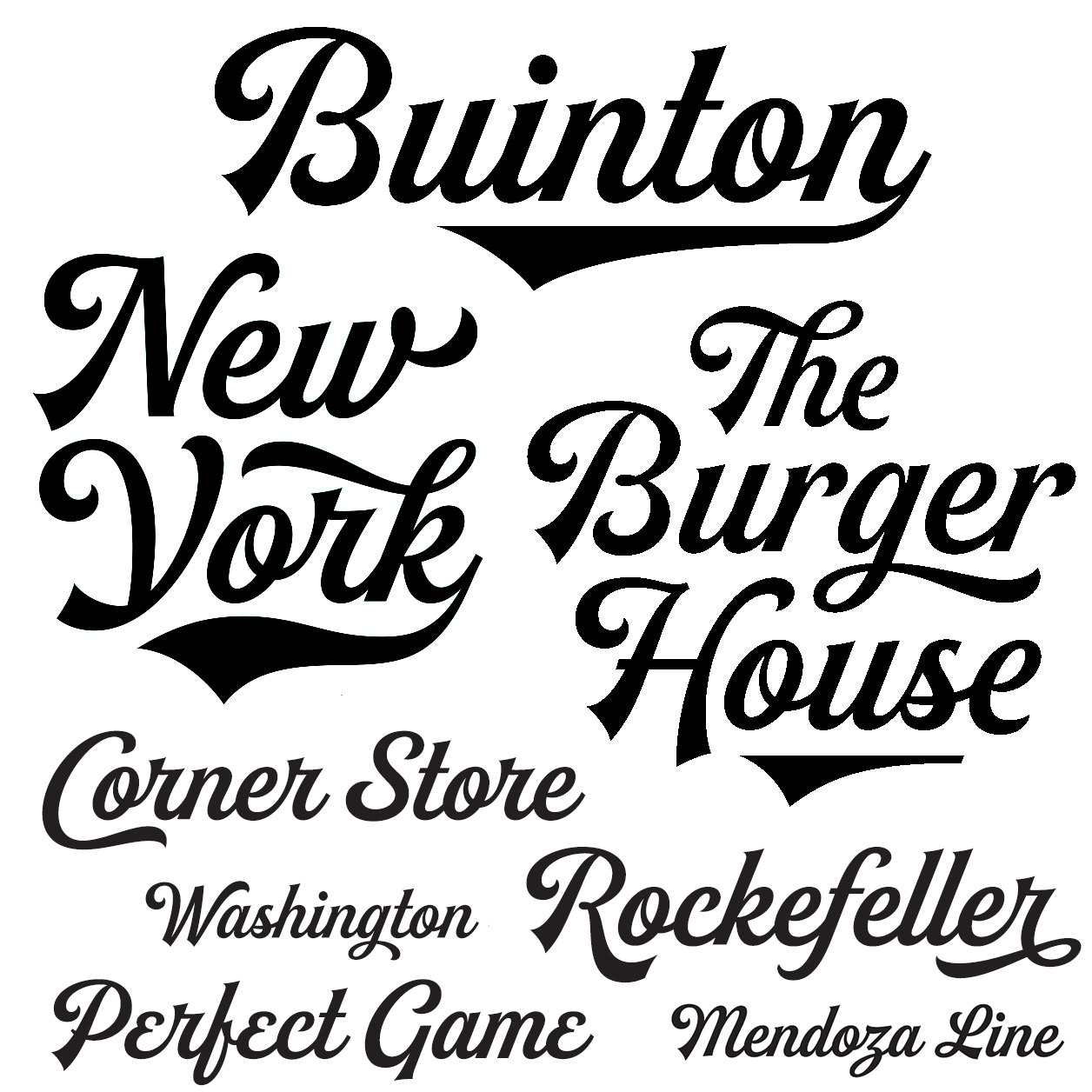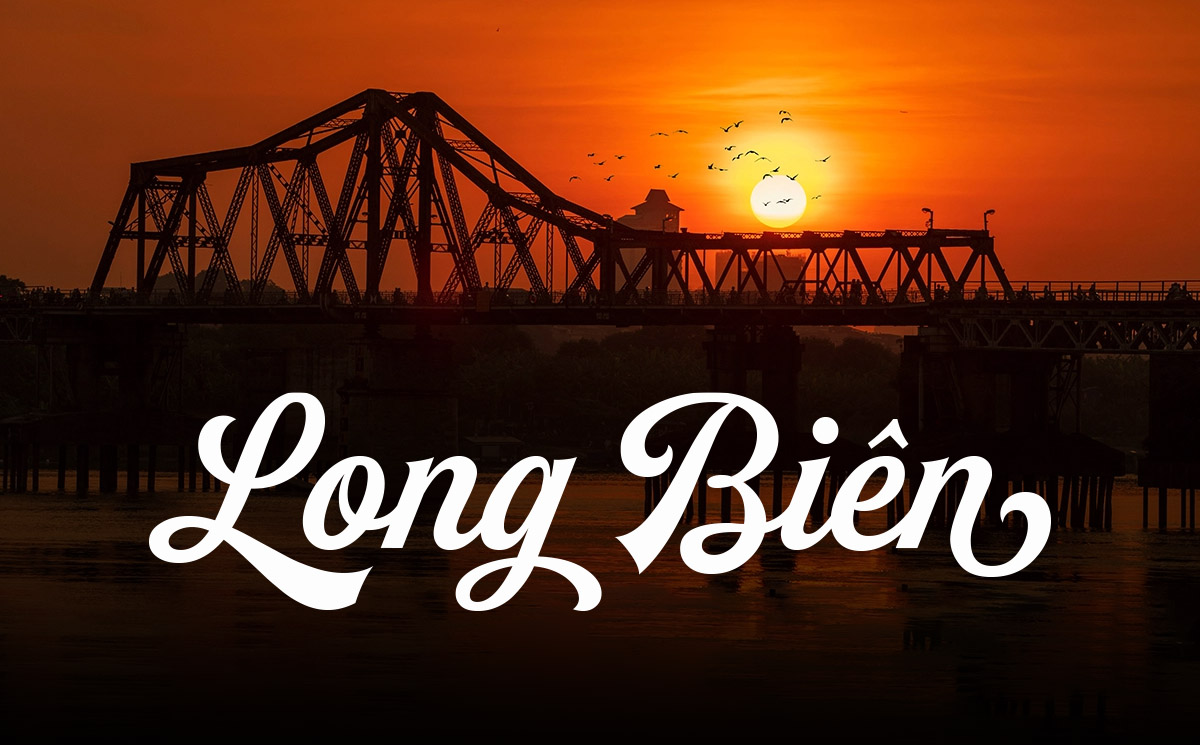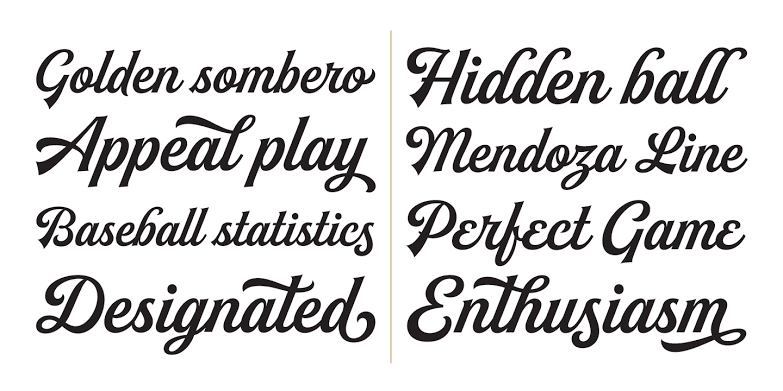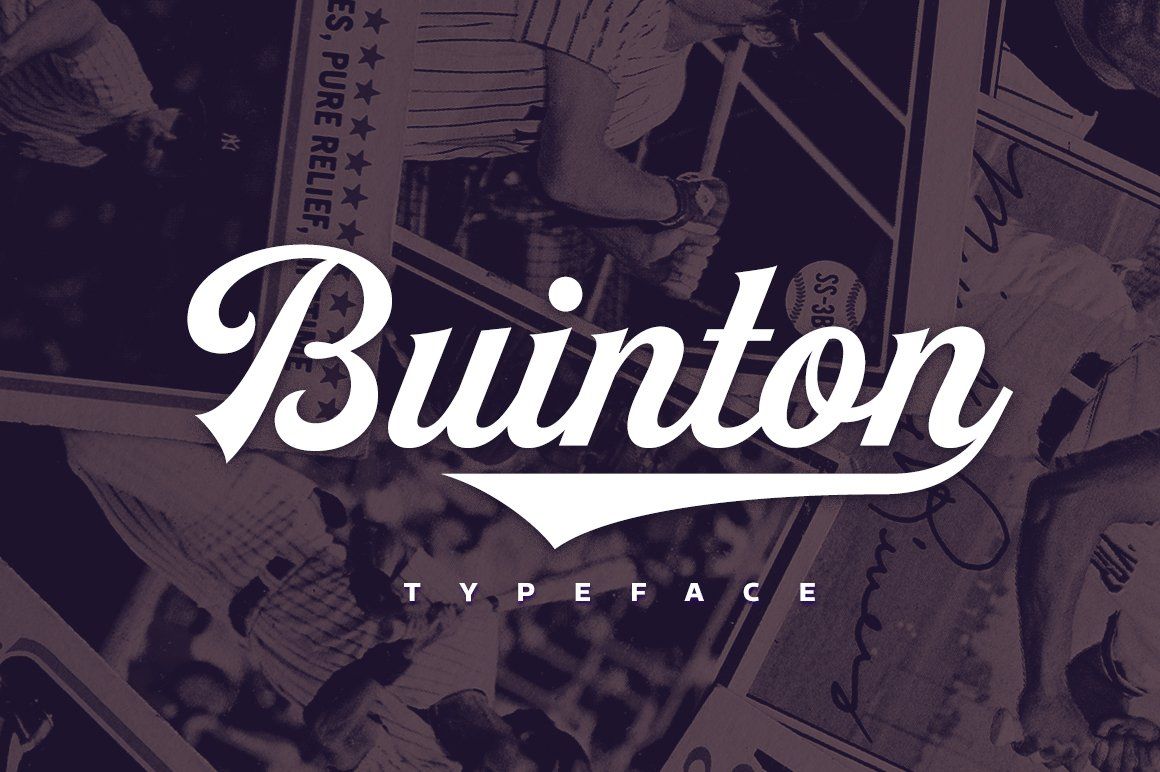
SVN Buinton là bộ phông chữ thuộc dòng Script mang đậm phong cách cổ điển (Vintage Retro), nổi bật với những đường nét uốn lượn quý phái, thanh lịch và cấu trúc chữ vô cùng chỉn chu. Được sáng tạo bởi nhà thiết kế Mika Melvas và được đội ngũ SVN tinh chỉnh hoàn chỉnh hệ thống dấu tiếng Việt, Buinton là lựa chọn hàng đầu cho các thiết kế logo nhãn rượu, bao bì cà phê hảo hạng, biển hiệu tiệm cắt tóc cổ điển và hộp quà tặng cao cấp. Doozypack.vn chia sẻ link download font SVN Buinton Việt hóa chuẩn kỹ thuật, giúp bạn sở hữu phông chữ đẳng cấp mà không lo gặp bất kỳ lỗi hiển thị dấu thanh nào khi thiết kế in ấn.
Đặc điểm thẩm mỹ độc đáo của bộ font SVN Buinton
Buinton tái hiện trọn vẹn ngôn ngữ đồ họa sang trọng của thế kỷ 20, nơi vẻ đẹp thủ công và sự lịch lãm của quý ông được đặt lên hàng đầu.
Phong cách Script cổ điển quý phái với nhịp điệu hoàn hảo
Đặc trưng lớn nhất của SVN Buinton là sự cân bằng tuyệt vời giữa các nét nhấn đậm đà và những đường cong nối chữ mượt mà. Cấu trúc chữ có độ nghiêng chuẩn mực, các góc bo cong mềm mại nhưng không hề ẻo lả, tạo nên một cảm giác chững chạc, uy tín và vững chãi. Khi sử dụng phông chữ này làm tiêu đề trên bao bì, thương hiệu của bạn sẽ ngay lập tức toát lên vẻ lâu đời, đắt giá và đậm chất nghệ nhân.
Hệ thống ký tự thay thế (Alternates) và nét uốn (Swashes) xa hoa
Một điểm khiến các nhà thiết kế luôn săn đón Buinton chính là kho ký tự trang trí vô cùng phong phú. Phông chữ cung cấp rất nhiều nét móc đuôi (tails), nét xoắn đầu chữ và các ký tự ghép đôi (ligatures) tinh xảo. Bạn có thể dễ dàng biến tấu một từ ngữ đơn giản thành một biểu tượng Typography độc bản mang dấu ấn riêng biệt mà không mất nhiều thời gian căn chỉnh phức tạp.
Ưu điểm nổi bật của bản font SVN Buinton Việt hóa
Khi ứng dụng các phông chữ trang trí cao cấp vào thị trường trong nước, sự chỉn chu về dấu câu là yếu tố quyết định đến tính chuyên nghiệp của bản thiết kế:
- Khắc phục triệt để lỗi dấu tiếng Việt: Phiên bản font SVN Buinton Việt hóa đã được tinh chỉnh thủ công từng dấu câu. Các dấu sắc, huyền, hỏi, ngã, nặng được vẽ với độ dày và độ nghiêng hoàn toàn ăn khớp cùng thân chữ gốc, không tạo cảm giác chắp vá hay va chạm vào các nét uốn lượn xung quanh.